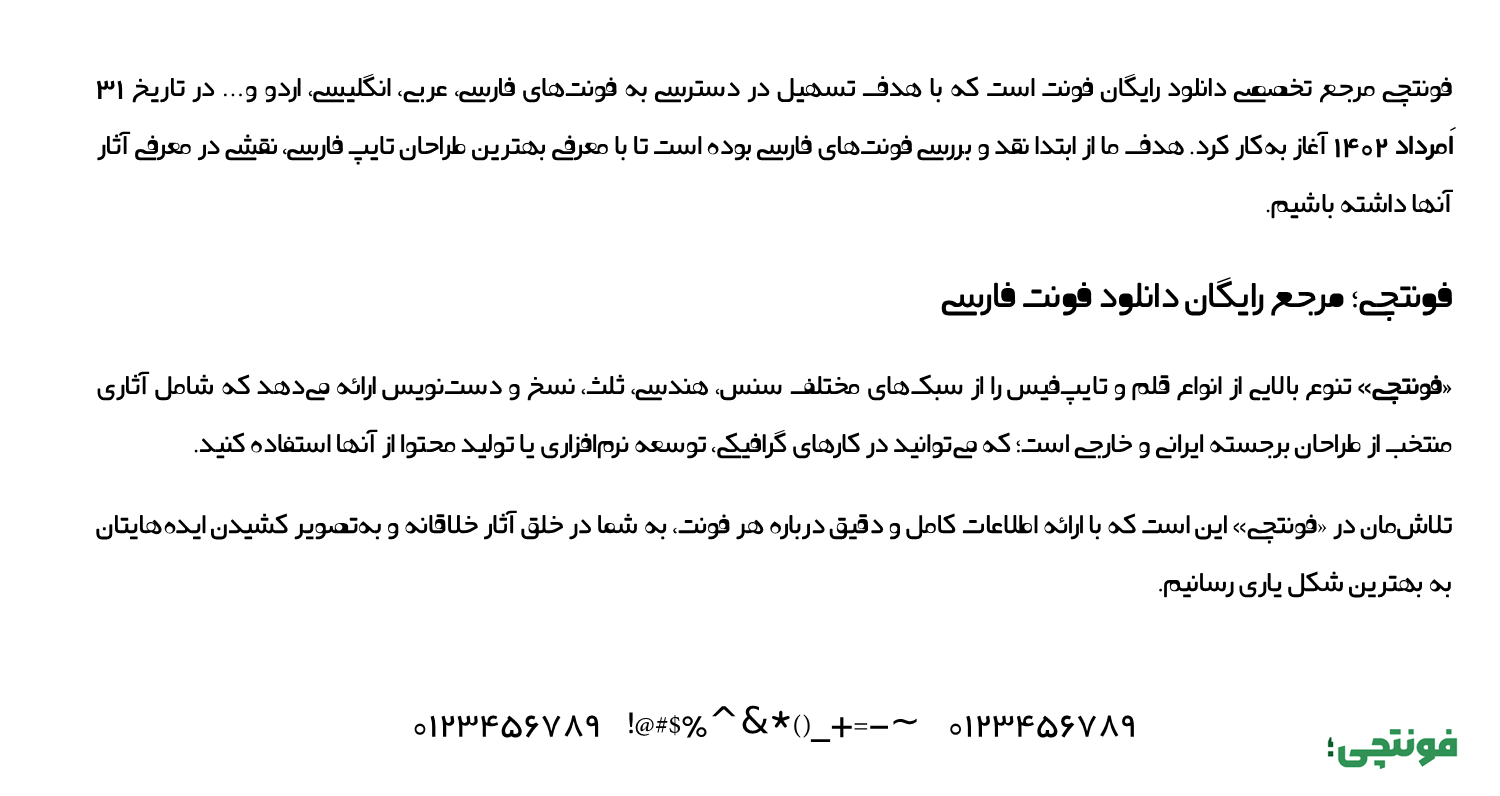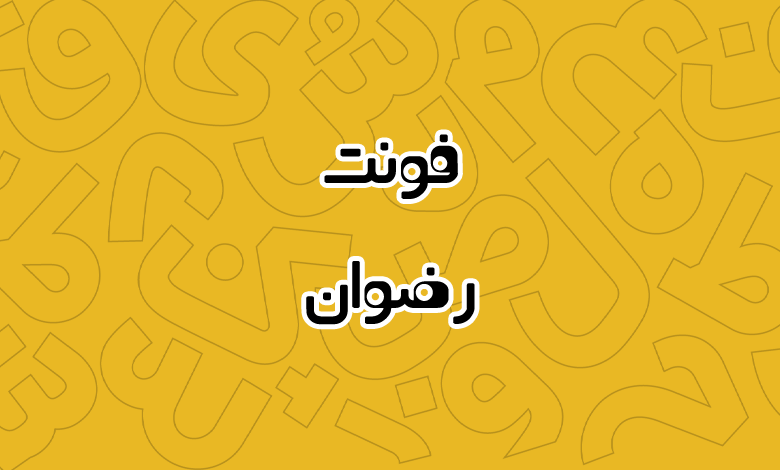
فونت رضوان (A Rezvan)
فونت رضوان (به انگلیسی: A Rezzvan) از قلمهای پرطرفدار آزاد فارسی است که با سبکی گرافیکی و فانتزی طراحی شده است. از این فونت میتوانید در پروژههایی که نیاز به یک فونت عنوان و نمایشی دارید استفاده کنید که بیشتر شامل چاپ بنر میشود. در ادامه با دانلود فونت رضوان رایگان همراه شما هستیم.
فونت رضوان توسط علی سواری طراحی شده و از دو وزن پشتیبانی میکند که جزو معدود فونتهای فارسی با حروف متغیر برای نمایشی کردن کلمات است. این فونت تمامی فرمتهای رایج برای استفاده را شامل میشود.
فونت رضوان فارسی به لطف یکسان بودن رسمخط با زبان عربی نیز سازگاری کامل دارد. بهطوریکه تمامی اعراب، حروف متفاوت عربی مانند «ک، ی، ه، ؤ، ئ» و اعداد متفاوت «۰۴۵۶» دارای گلیف اختصاصی خود هستند. از این فونت میتوانید در پروژههای دوزبانه فارسی و عربی استفاده کنید.
ساختار طراحی فونت رضوان بهصورت کاملا گرافیکی است. در حروفی مانند «ه، م، ق، ف، ص» که دارای چشمی هستند، شاهد نازک شدن بخشی از چشمی هستیم که ظاهر فونت را نمایشی کرده است. از طرفی دیگر برخی ترکیبات مانند «ـی» اجبارا دارای ترکیب متغیر هستند. میتوانید برای برخی ترکیبات دیگر مانند «صی، شی، ضی و…» نیز از ترکیبات متغیر استفاده کنید.
فونت رضوان برای زبان انگلیسی فاقد طراحی اختصاصی است و از فونت پیشفرض برای تایپ حروف لاتین استفاده خواهد شد. این فونت از دو وزن مختلف پشتیبانی میکند:
- A Rezvan Regular: این نسخه معمولی فونت رضوان است.
- A Rezvan Fat: نسخه چاق یا بولد فونت رضوان تنها تفاوتی که با نسخه معمولی دارد، توپر بودن چشمیها در گلیفهای آن است.
با توجه به سبک طراحی و ظاهری که فونت Rezvan دارد از این قلم میتوان در متون کوتاه بهترین استفاده را داشت. این فونت برای عناوین و تبلیغات گزینه مناسبی است و پیش از اینکه شاهد تنوع بالایی در فونتهای پولی فارسی باشیم، از این فونت بهوفور در کارهای تبلیغاتی، خصوصا چاپ بنرهای سطح شهر استفاده میشد.